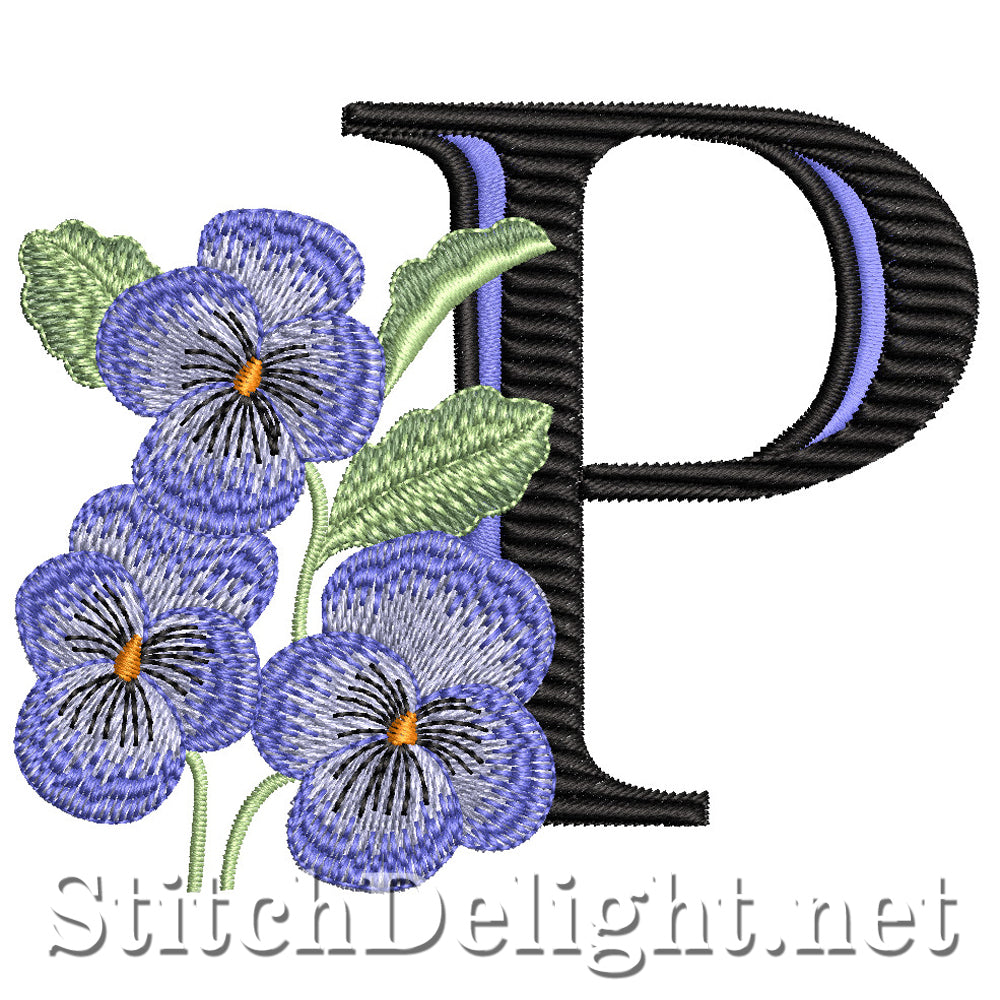
Police de caractère violet SDS1516 P
Cette magnifique lettre simple Pansy violette est un MUST HAVE ! Cette police a une hauteur moyenne de 2,7" donc elle fonctionne même avec le plus petit cerceau 4x4.